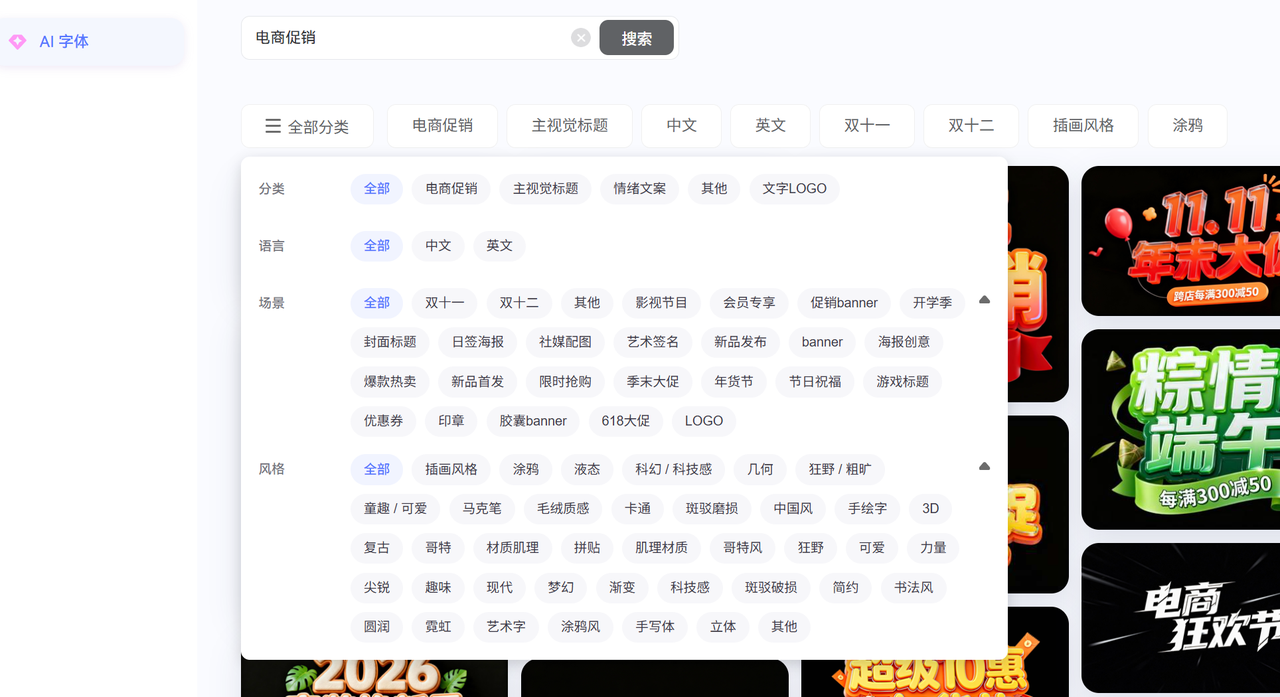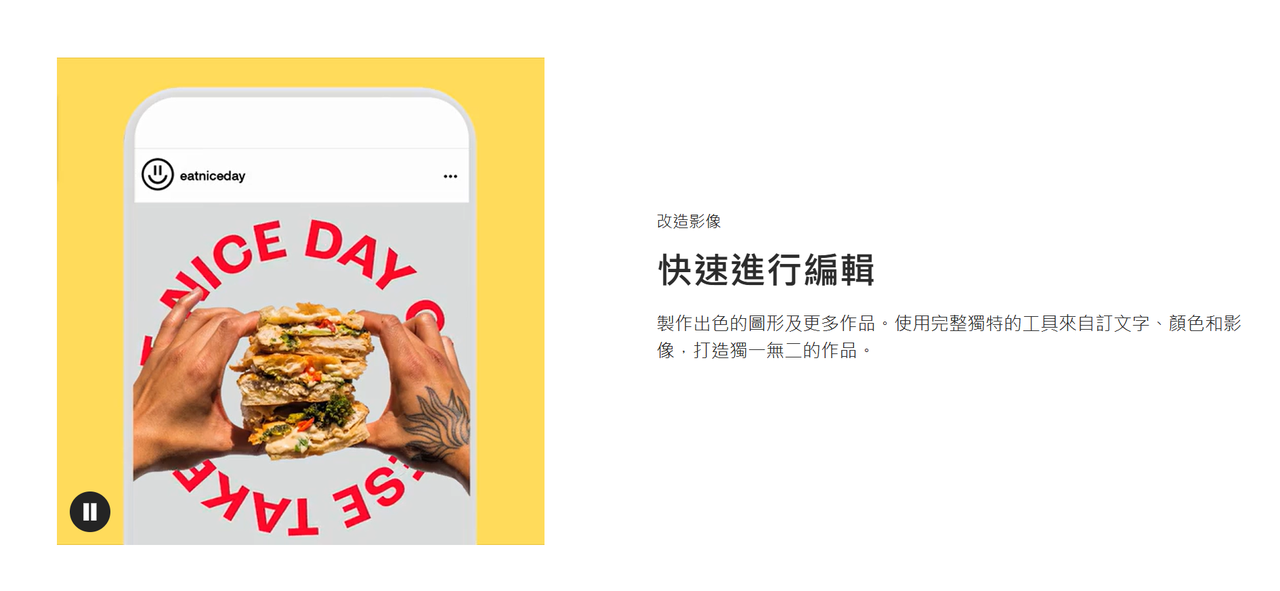
如何制作电商促销字体?分享 4 款好用的字体工具
字体在电商这个视觉为王的战场上,是非常重要的因素。一个好的促销字体,不仅能传达商品信息,更能烘托氛围、激发购买欲望。很多朋友可能觉得“字体设计”听起来很高深,但别担心,我今天就是来给大家“降维打击”的,推荐一些无论是设计小白还是进阶达人,都能轻松上手的电商促销字体制作工具。
1. 字由 AI 生成字体
是的,最近两年 AI 发展非常迅速,字体设计行业也不例外,字由的 AI 生成字体功能,可以让你没有设计基础的情况下,快速完成字体生成。
1. 访问 AI 生成字体功能页面
1. 根据需求,进行筛选模板
AI 生成字体提供了多种筛选维度,您可以根据自己的需求,对“分类”、“语言”、“场景”、“风格”等维度进行筛选。
1. 选择模板,更换文案,一键生成
选择好模板后,您可以自定义自己的文案,点击生成,就能快速生成和模板一样的字体。
1. 下载原图,进行使用
1. Adobe Photoshop
Adobe Photoshop,简称PS,大名鼎鼎的图像处理软件,相信大家就算没用过也肯定听过它的名字在电商促销字体制作方面,PS以其无与伦比的图层、滤镜和混合模式功能,能够让文字产生各种令人惊艳的视觉效果,无论是模拟真实材质、打造光影特效,还是进行复杂的图像合成,PS都能游刃有余。它就像一个魔法盒,只有你想不到的,没有它做不到的。对于追求极致视觉表现和个性化设计的电商卖家来说,PS无疑是首选的专业工具。
PS制作文字特效的时候,可以通过内发光、外发光、斜面和浮雕、描边、投影、颜色叠加、渐变叠加、图案叠加等多种图层样式,可以模拟出金属、玻璃、霓虹灯、毛绒、冰雪等各种材质和光影效果。
1. Adobe Illustrator
同样是 Adobe 旗下的 Adobe Illustrator,简称AI,是专业的矢量图形设计软件。与PS处理像素图像不同,AI处理的是矢量图形,这意味着你用AI制作的任何图形,包括文字,无论放大多少倍都不会出现锯齿或模糊,始终保持清晰锐利。这对于电商促销中需要反复缩放、应用到不同尺寸和媒介(如海报、详情页、Logo)的字体设计来说,简直是太完美了!比如你想创建可无限缩放的自定义字体Logo、独特的促销标题,或是对现有字体进行深度的造型改造,就可以试试 Adobe Illustrator。
Adobe Illustrator 可以通过钢笔工具,绘制和修改文字的轮廓,将普通字体转化为独特的自定义字形。将文字转换为可编辑的矢量路径后,你可以像操作其他图形一样,对文字的每一个笔画进行修改、变形、甚至局部添加细节,实现真正的“字体设计”。
1. Canva/创客贴/稿定设计
Canva(国内也有很多类似的在线设计平台,比如“创客贴”、“稿定设计”等,功能大同小异,我这里就以Canva为例)是一个非常简单方便的在线设计工具,它将专业设计变得触手可及。对于没有设计基础但又想快速制作出高颜值促销字体的电商卖家来说,Canva 它提供了海量的模板、字体、图片和设计元素,通过简单的拖拽和编辑,你就能在几分钟内制作出专业的促销海报、Banner和社交媒体图片,其中当然也包括各种吸睛的字体效果。
canva针对电商、社交媒体、广告等场景,提供了成千上万的精美模板,直接套用修改文字和图片即可。canva拥有大量的免费和付费字体,涵盖各种风格,并支持字体组合推荐。通过描边、阴影、曲线、渐变等多种文字效果预设,一键即可应用。
总结
虽然 PS 和 Adobe Illustrator 能很好的完成字体的设计,但使用门槛很高,即使专业的设计人员,也比较耗时。Canva、创客贴等在线设计工具,虽然降低了使用门槛,但字体设计的效率依然不高,对于一些非设计专业的小伙伴,还是需要很长的时间才能实现。字由 AI 生成字体的功能很好的解决了这个问题,只需要根据你的需求选择合适的模板,然后输入自己的文案,就能一键完成字体的设计,大家可以试试字由的 AI 字体生成功能。